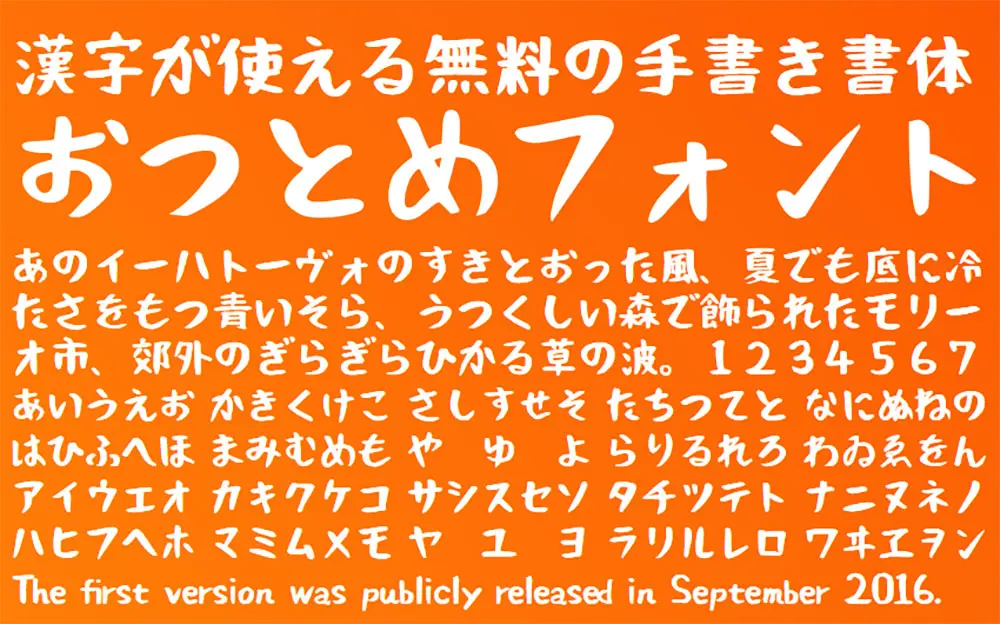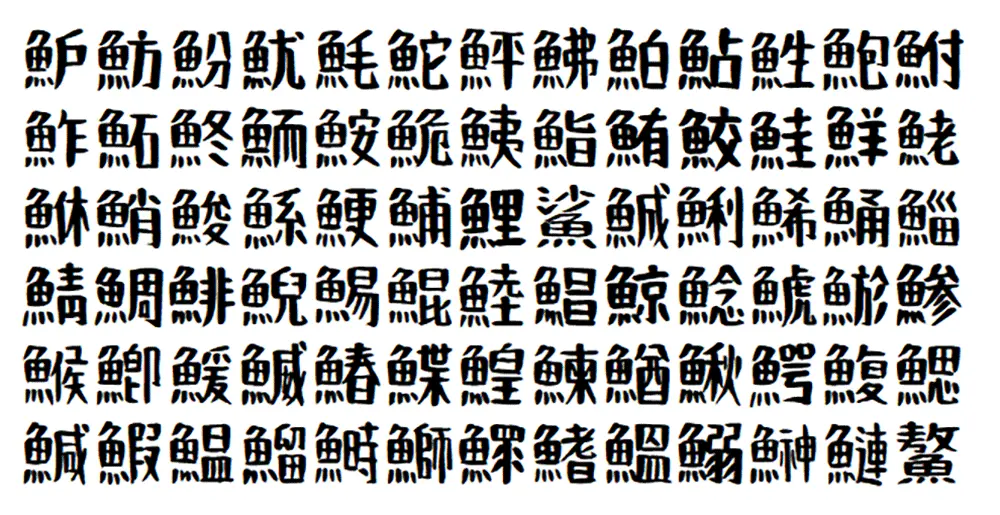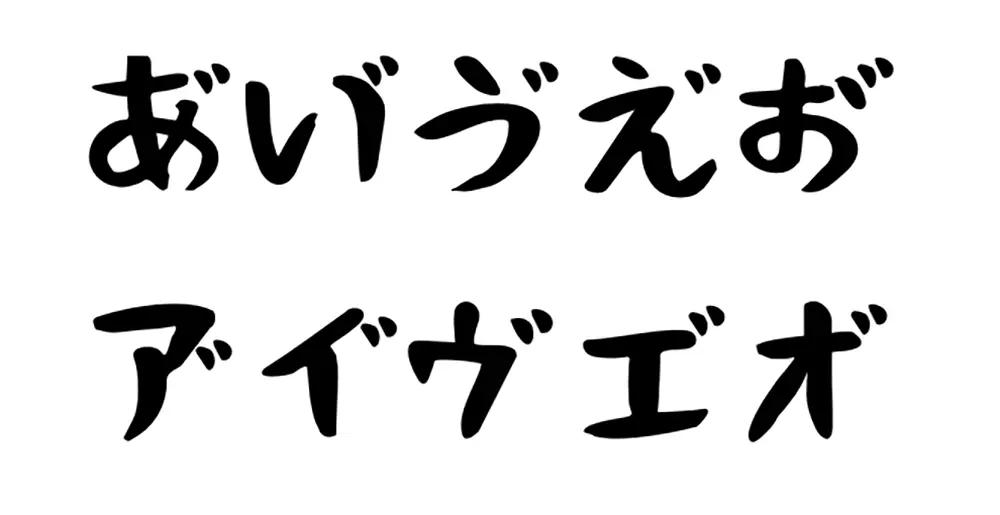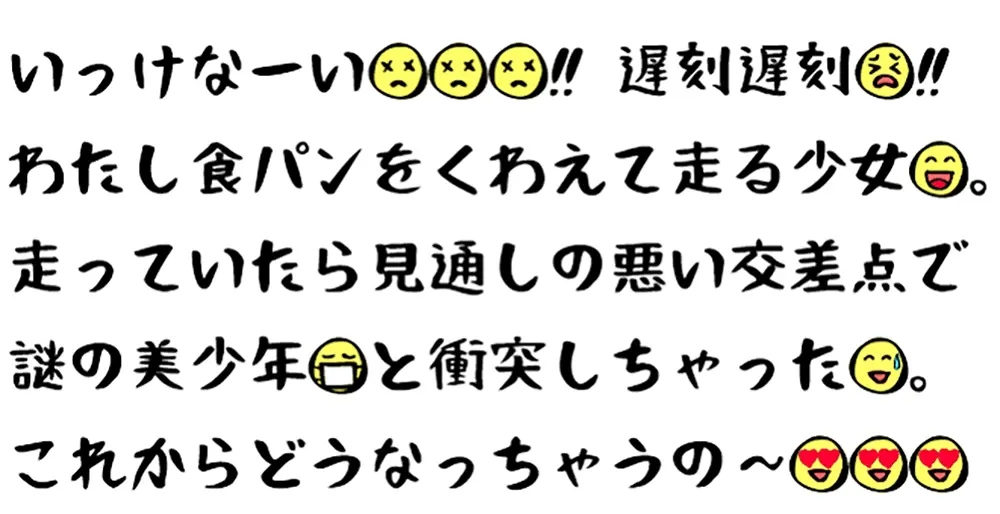
おつとめフォント是以毛筆手寫的文字為基礎製作的日語免費字體。漢字收錄了JIS基本漢字(6355字)等約9000字。商用使用也是可以的。
對於現代人來說,毛筆字體不是可讀性很好的字體。但是,諸如“寄色”和“關帝流”等高度可見的字符經常用於促銷傳單和貼紙。因此,本字體是根據書法文字的實際使用情況,重視“高可視性”而製作的。
雖然是很有獨特的手寫文字,但是在商務使用中也可以免費使用,是很划算的“禮物”,請嘗試一次。
收錄了很多漢字:收錄了JIS基本漢字(6355字)等約9000字的漢字。光是“魚俱樂部”一詞就有 100 多個漢字,從興趣創作活動到廣告傳單等商業作品都可以用於多用途。
JIS基本漢字(6355字)など約9000字の漢字を収録しています。魚部(さかなへん)の漢字だけでも百種類以上収録しているので、趣味の創作活動から広告チラシなどの商業製作物まで多用途に使用することが出來ます。
可以輸入A行的假名:通過連續輸入 A 行的假名和濁音標記(゛),可以輸入 A 行的濁音標記假名。只能使用支持連字功能的軟件輸入。
あ行の仮名と濁點(゛)と続けて入力することあ行の濁點仮名を入力することが出來ます。合字機能に対応しているソフトでのみ入力可能です。
通過並用姊妹字體,可以實現更豐富的表達:通過安裝與 Otsutome 字體配合使用的表情符號字體“Otsutome Emoji”,可以實現更豐富的表情。請注意,只有部分軟件支持“乙女表情符號”的彩色顯示。
おつとめフォントとの併用を前提に製作した絵文字フォント「おつとめEmoji」もあわせてインストールすることで、より豊かな表現が可能になります。なお「おつとめEmoji」のカラー表示は一部のソフトのみ対応しています。